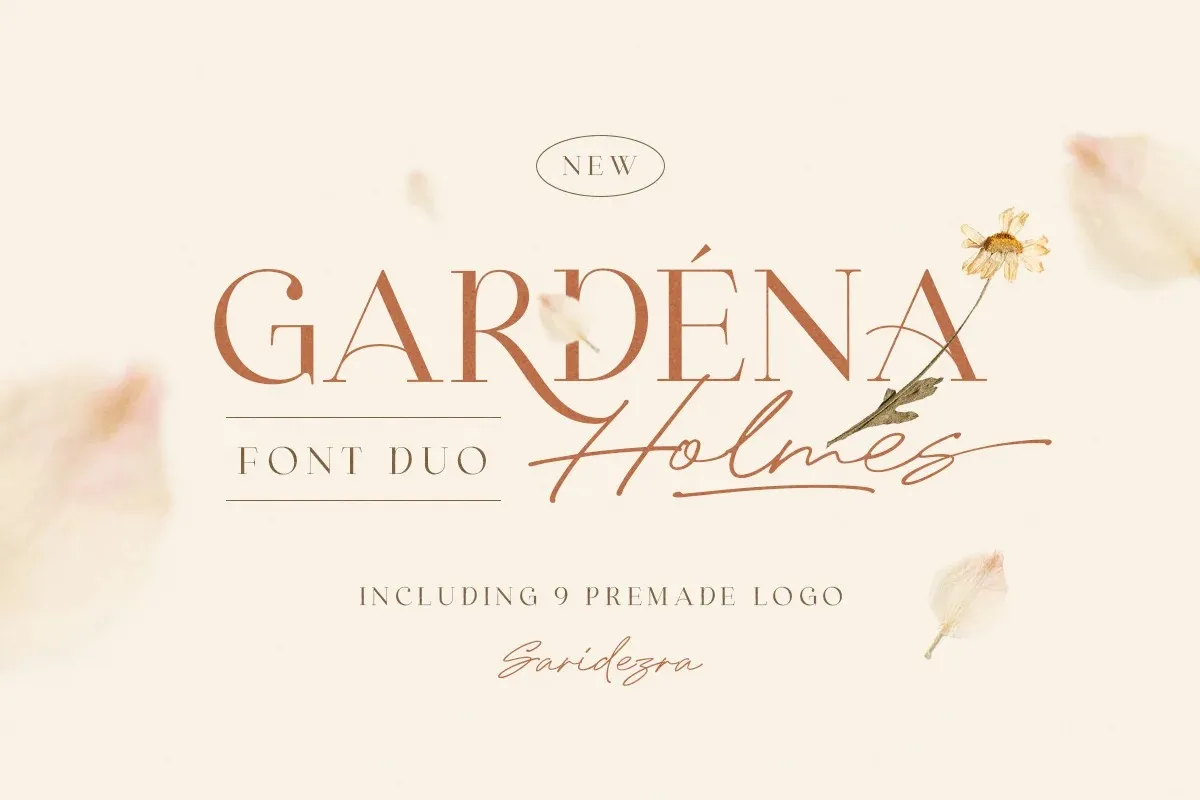
Gardena Holmes Font – Download Grátis
A Gardena Holmes Font é uma elegante e moderna fonte escrita a mão com efeito de traço de caneta rápida. Ela oferece duas fontes: uma serifada delicada e um script livre à mão, ambos perfeitamente adequados para aplicações multilingues, incluindo números e símbolos. Este conjunto duplo também suporta vários ligamentos, permitindo-lhe criar escritas sofisticadas. Além disso, a Gardena Holmes Font já está codificada em PUA (Unicode Private Use Area), o que significa que ela pode ser utilizada em uma variedade de contextos sem problemas. Como um toque adicional de criatividade e economia de tempo, vem incluso com seis belas logomarcas prontas para uso, tornando a criação de um logotipo muito mais fácil e intuitiva.